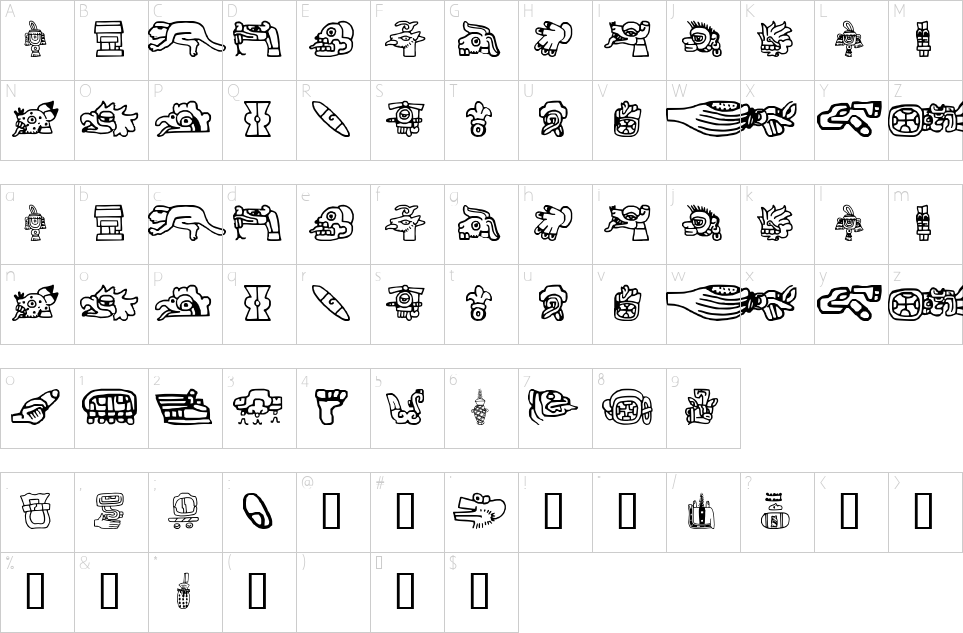
Aztec Font
A fonte Aztec é uma criação audaz e única, ideal para quem busca uma fonte que destaque sua personalidade em qualquer projeto. Desenhada por No Images Fonts, a Aztec oferece uma mistura de simplicidade e sofisticação que se adapta bem a diversos estilos de design. Seja para criar design gráfico, criação de websites ou até mesmo para escrita de letras ao vivo, a aztec é uma escolha inteligente. Com um design geométrico e vibrante, ela captura o espírito do azteca, incorporando elementos arquitetônicos e formas geométricas que criam um estilo único. Embora não seja uma fonte clássica, a Aztec traz uma sensação de modernidade e originalidade, tornando-a uma opção atraente para aqueles que desejam um visual inovador em seus projetos. Com seu design original, a fonte Aztec é uma opção certeira para quem deseja uma fonte única e autêntica, sem ter de se preocupar com custos.